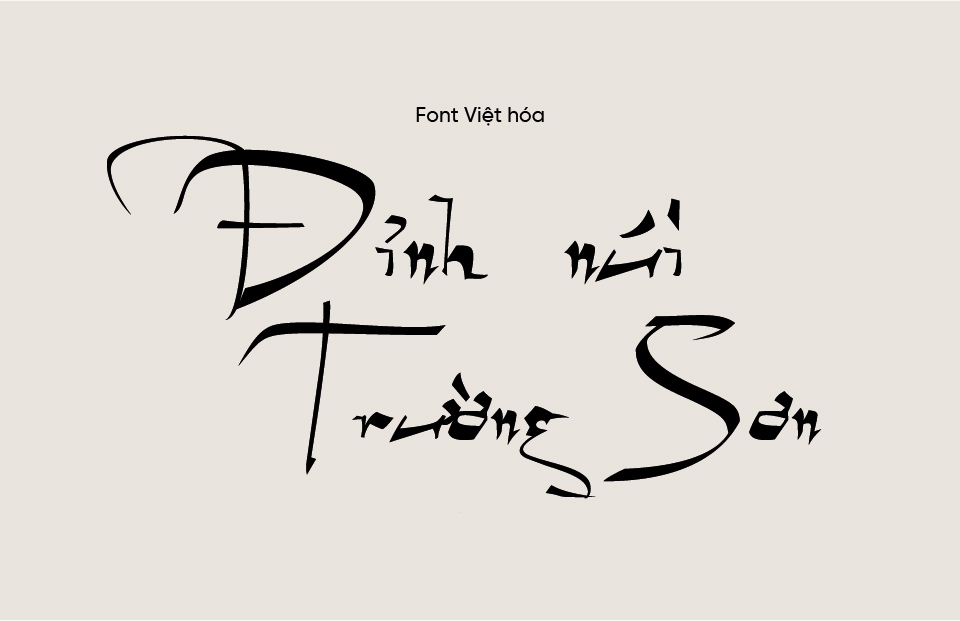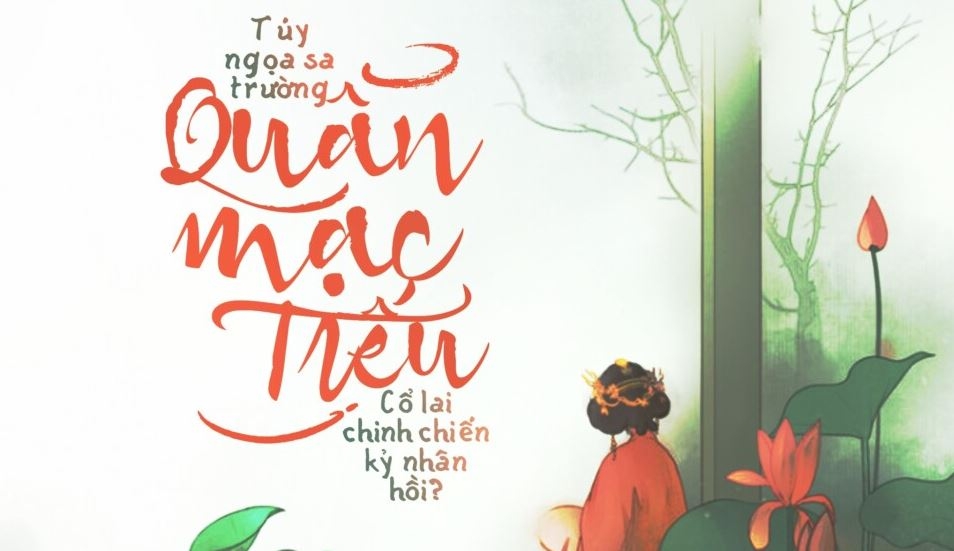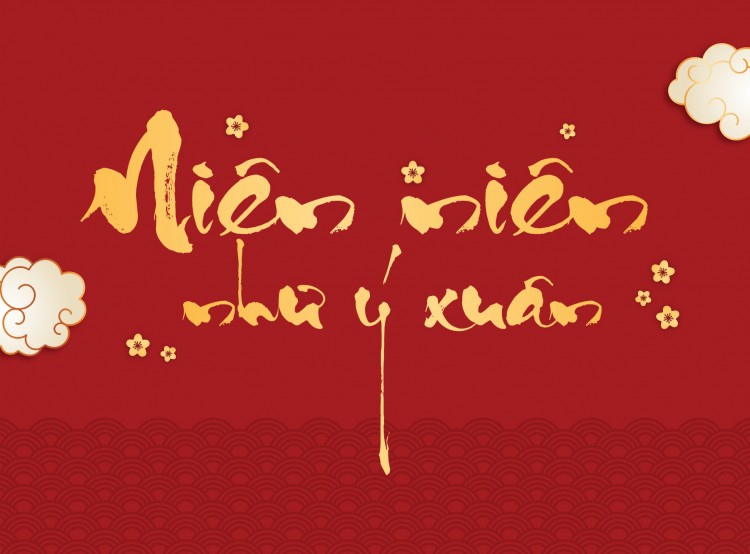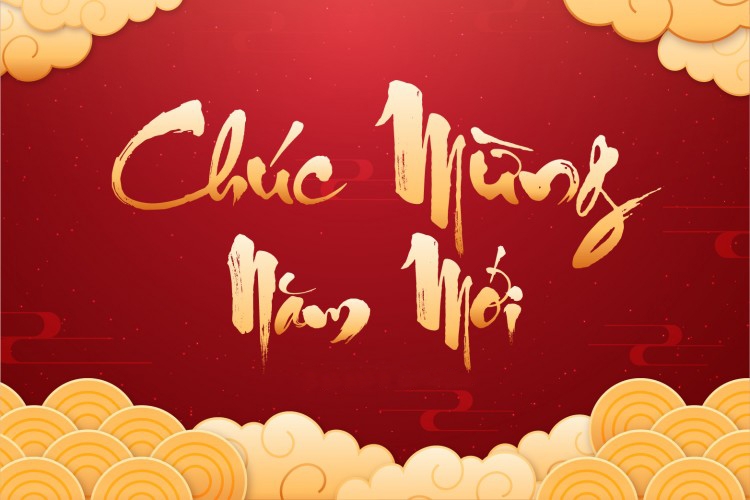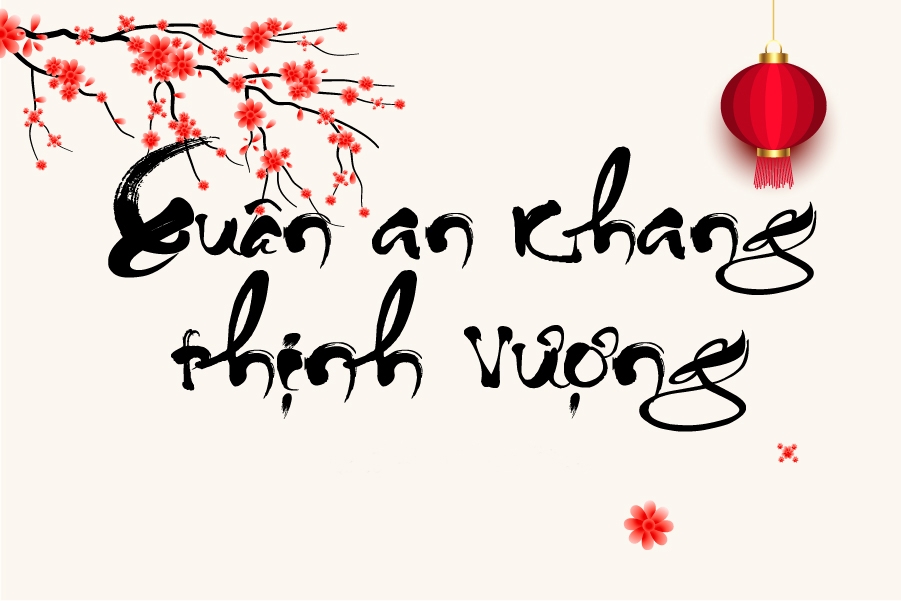
Tổng hợp 75 Font thư pháp đẹp
Font chữ thư pháp là kiểu chữ được lấy cảm hứng từ nghệ thuật viết tay truyền thống, với những đường nét uyển chuyển, mềm mại và đầy chất thơ. Mỗi ký tự như mang theo hơi thở của thời gian, gợi nhắc đến vẻ đẹp cổ điển và tinh thần nghệ thuật Á Đông. Trải qua sự phát triển của thiết kế hiện đại, font thư pháp ngày càng được ứng dụng linh hoạt và sáng tạo trong nhiều lĩnh vực: từ thiệp mời, bìa sách, logo, đến các sản phẩm truyền thông mang đậm bản sắc văn hoá. Chính sự giao thoa giữa tính truyền thống và tính thẩm mỹ đương đại đã làm nên sức hút độc đáo cho dòng font này.
Giới thiệu về font chữ thư pháp
Font chữ thư pháp gây ấn tượng mạnh bởi những đường nét uốn lượn tinh tế, mang đến vẻ đẹp riêng biệt, đầy chất nghệ. Điểm đặc trưng nổi bật của loại font này chính là sự tự do trong bố cục và cách thể hiện ký tự — nơi người sáng tạo có thể thể hiện sự phóng khoáng, linh hoạt và cá tính nghệ thuật của mình.
Phần lớn các font thư pháp được thiết kế theo phong cách cổ điển, gợi cảm giác hoài niệm, sang trọng và tôn vinh giá trị truyền thống. Đây là lý do font thư pháp thường xuất hiện trong các thiết kế mang tính nghệ thuật như: thiệp mời, logo, tiêu đề sách, bao bì sản phẩm thủ công hay các ấn phẩm quảng bá văn hoá.
Ngày nay, nhờ sự hỗ trợ của công nghệ, hàng trăm bộ font thư pháp đã được phát triển và Việt hóa, giúp người dùng dễ dàng tìm kiếm và ứng dụng tùy theo nhu cầu. Bạn có thể tải về từ các trang chia sẻ font hoặc sử dụng trực tiếp trong các phần mềm thiết kế chuyên dụng như Adobe Illustrator, Photoshop, hay thậm chí là các công cụ thiết kế trực tuyến.
Tổng hợp các loại font thư pháp đẹp
Font chữ Geza Script
Là một trong những font chữ thư pháp được Việt hóa hoàn chỉnh, MTD Geza Script gây ấn tượng với những đường nét thanh mảnh kết hợp đậm – nhạt hài hòa. Font sở hữu chút cứng cáp ở một số ký tự, tạo nên phong cách thư pháp hiện đại, mạnh mẽ nhưng vẫn mềm mại, rất phù hợp trong thiết kế tiêu đề, poster hay thiệp mời mang phong cách nghệ thuật.
Font chữ Coffee Break Script
Tiếp theo là MTD Coffee Break Script, một font mang hơi thở cổ điển với nét chữ uyển chuyển, nhẹ nhàng. Phông chữ này đặc biệt thích hợp cho các thiết kế bìa sách, tiểu thuyết lãng mạn, tranh thư pháp nghệ thuật, mang lại cảm giác thanh lịch và sâu lắng cho người xem.
Font chữ Quang Ninh
Ra mắt lần đầu năm 2007 và cập nhật vào 2010, font chữ Quang Ninh là lựa chọn quen thuộc mỗi dịp Tết đến xuân về. Lấy tên chính tác giả làm tên font, Quang Ninh mang đậm hơi thở truyền thống, thể hiện sự tươi vui và rộn ràng trong từng nét bút. Font hiện đã chuyển sang bảng mã Unicode, tiện lợi hơn cho người dùng khi thiết kế thiệp Tết, tranh câu đối hay banner lễ hội.
Font chữ Thiên Ân
Được sáng tạo bởi Đinh Kiên, font Thiên Ân mang hình dáng chữ viết tay của các ông đồ xưa, mềm mại, hoài cổ và thấm đẫm chất thư pháp. Tên font cũng chính là tên con trai của tác giả, như một món quà ý nghĩa trao gửi tình cảm. Dựa trên ký tự thư pháp của Đăng Học, Thiên Ân là sự lựa chọn lý tưởng cho những ai muốn truyền tải chiều sâu và cảm xúc trong thiết kế.
Font chữ Thành Công
Một cái tên được yêu thích trong cộng đồng thiết kế Việt – font Thành Công. Được Việt hóa chỉn chu và cho phép sử dụng miễn phí, font này mang lại cảm giác “có hồn” với từng nét chữ bay bổng nhưng dứt khoát. Tên gọi cũng là cách tác giả thể hiện cá tính riêng, khơi gợi cảm xúc từ những đường nét tưởng chừng đơn điệu. Font thường được ứng dụng rộng rãi trong thiết kế thiệp Tết, câu đối, banner mừng xuân…